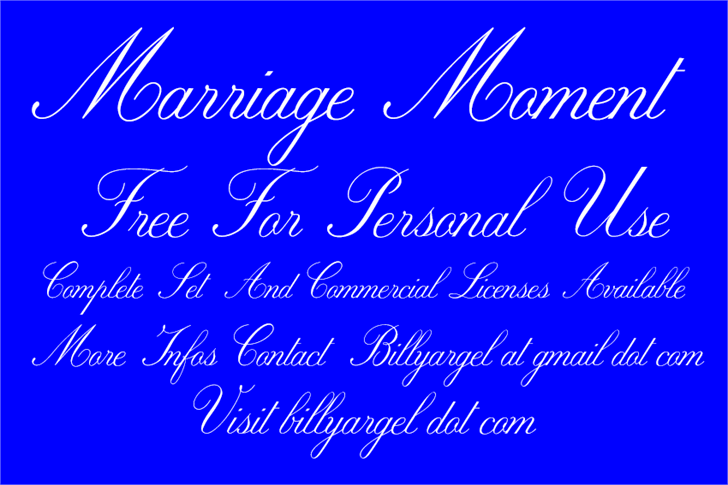
Marriage Moment Font – Download Grátis
A fonte ‘Marriage Moment Font’ foi criada pelo designer Billy Argel para ser usada na personalização de momentos especiais, especialmente casamentos. Esta fonte é a mão escrevendo e sua delicadeza torna-a perfeita para cartões de aniversário, lembranças familiares ou até mesmo adesivos para móveis. A proposta única da fonte ‘Marriage Moment’ reside em suas características curvilíneas fluidas, que criam um tom suave e aconchegante. Suas linhas variadas dão ao texto uma aparência natural, tornando-a perfeita tanto para nomes de casamento quanto para cartões personalizados. O design livre deste font, permitindo flexibilidade na aplicação, é ideal para quem busca algo diferente em suas criações. Com sua facilidade de uso e a combinação única de elegância e naturalismo, ‘Marriage Moment Font’ está repleta de personalidade, tornando-a uma escolha ótima para designers atentos aos detalhes. Não se surpreenda com seus resultados imediatos e únicos, seja em impressões digitais ou até mesmo gráficos a mão. Esse recurso font oferece uma excelente opção para quem busca algo personalizado que vai além da estética clássica. E é isso mesmo – não perca esta oportunidade única de criar algo único e autêntico, usando ‘Marriage Moment Font’. Visite o site oficial do designer Billy Argel para mais detalhes ou para adquirir a licença completa deste recurso font.